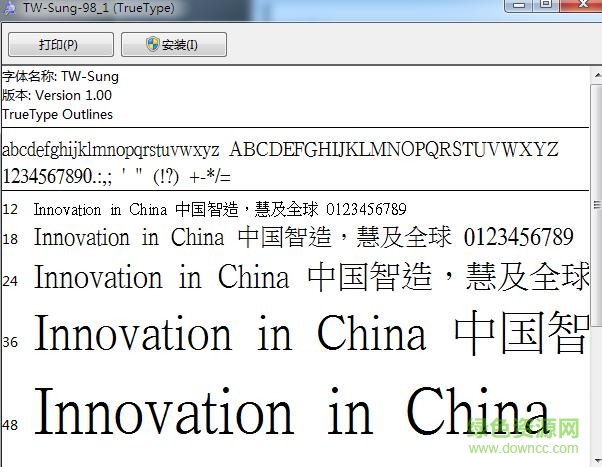
全字庫(kù)正宋體98
全字庫(kù)正宋體是一款清晰醒目的宋體字體,傳承了宋體字體的優(yōu)秀特點(diǎn),并加入系列字體自己的特色,讓字體更有韻味,感興趣的朋友歡迎下載使用!
全字庫(kù)正宋體簡(jiǎn)介
全字庫(kù)正宋體是全字庫(kù)系列字體中的一款,筆畫結(jié)構(gòu)十分對(duì)稱,字形清晰大方得體,適用于印刷包裝、廣告設(shè)計(jì)、平面設(shè)計(jì)、標(biāo)題正文等領(lǐng)域!
全字庫(kù)正宋體